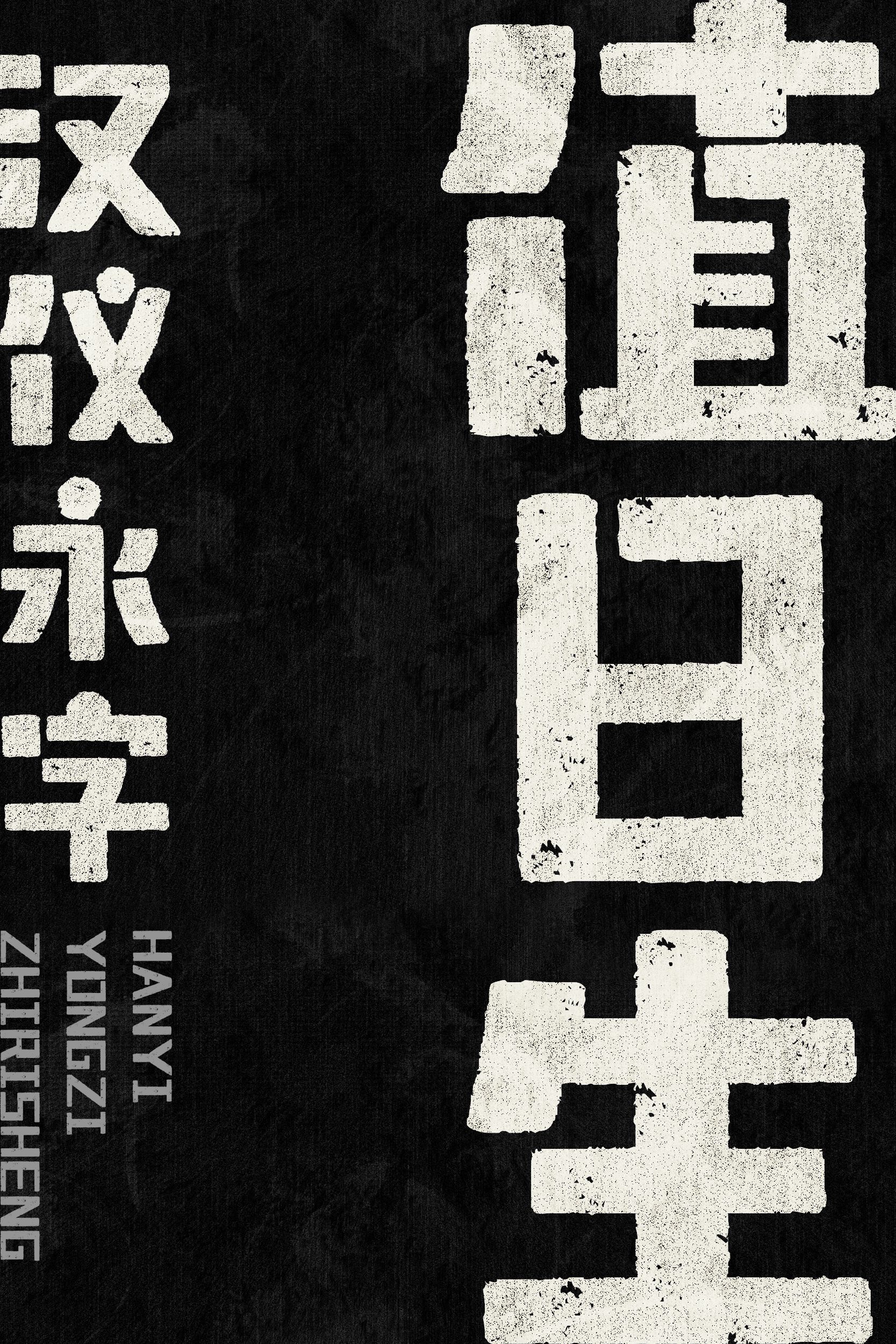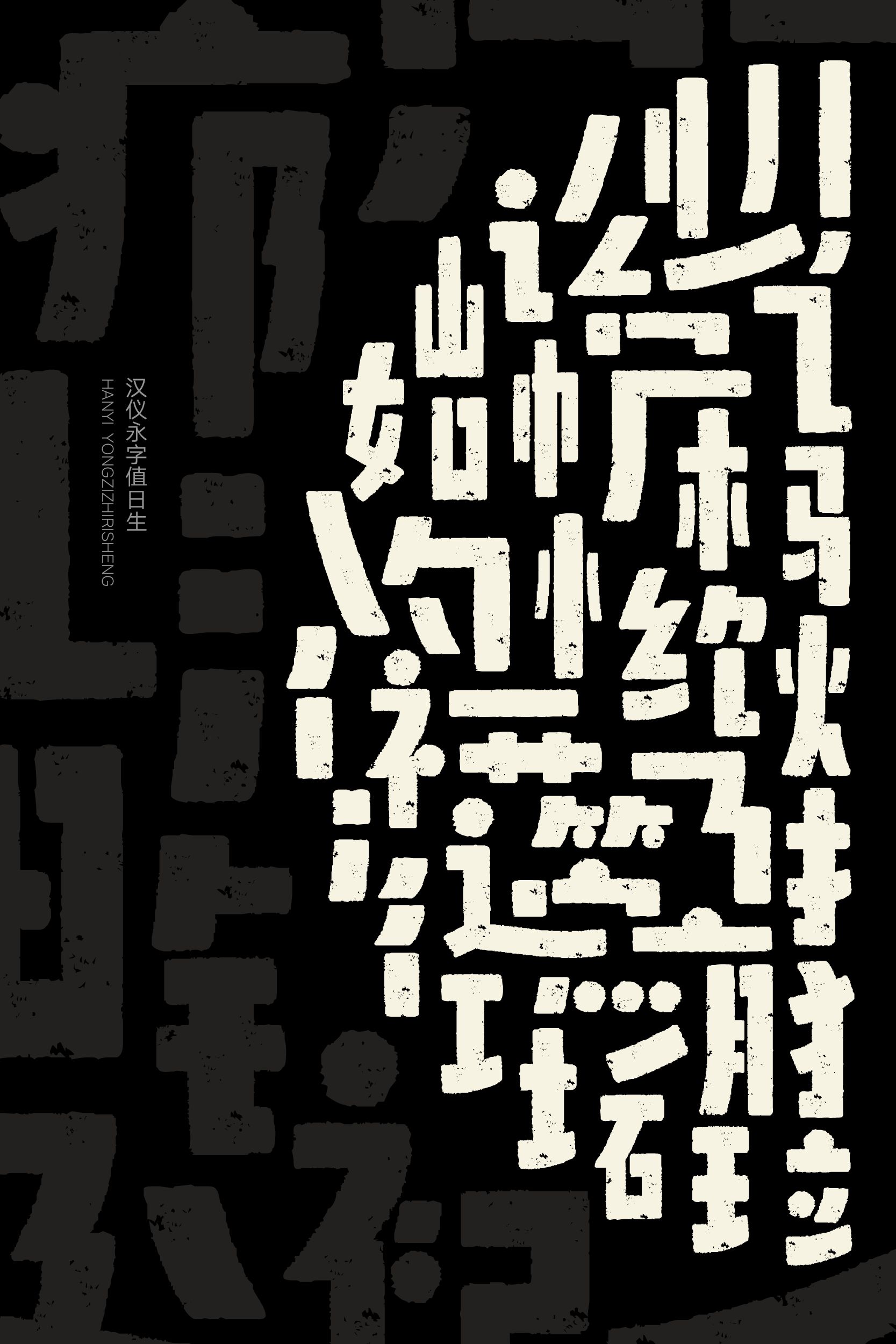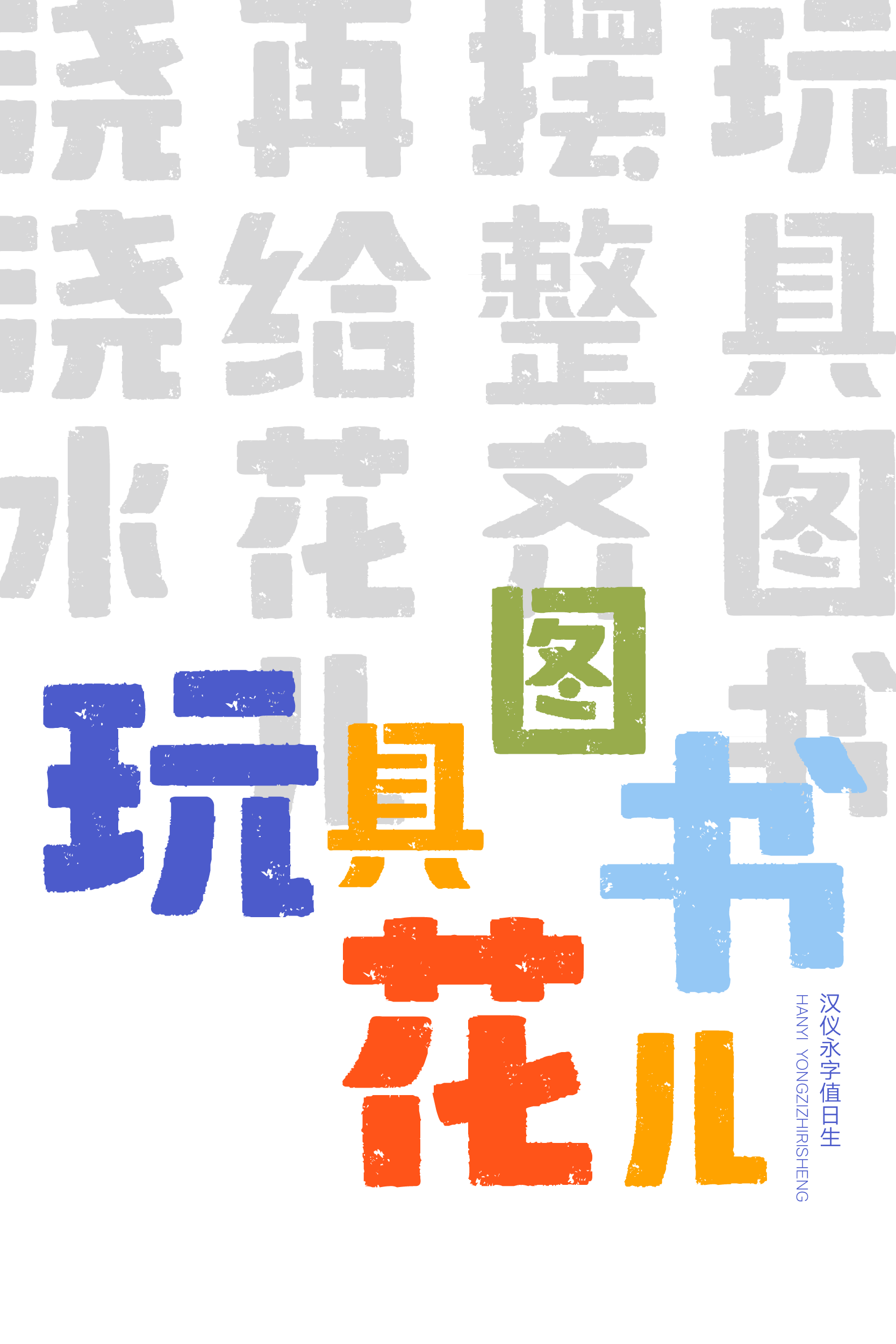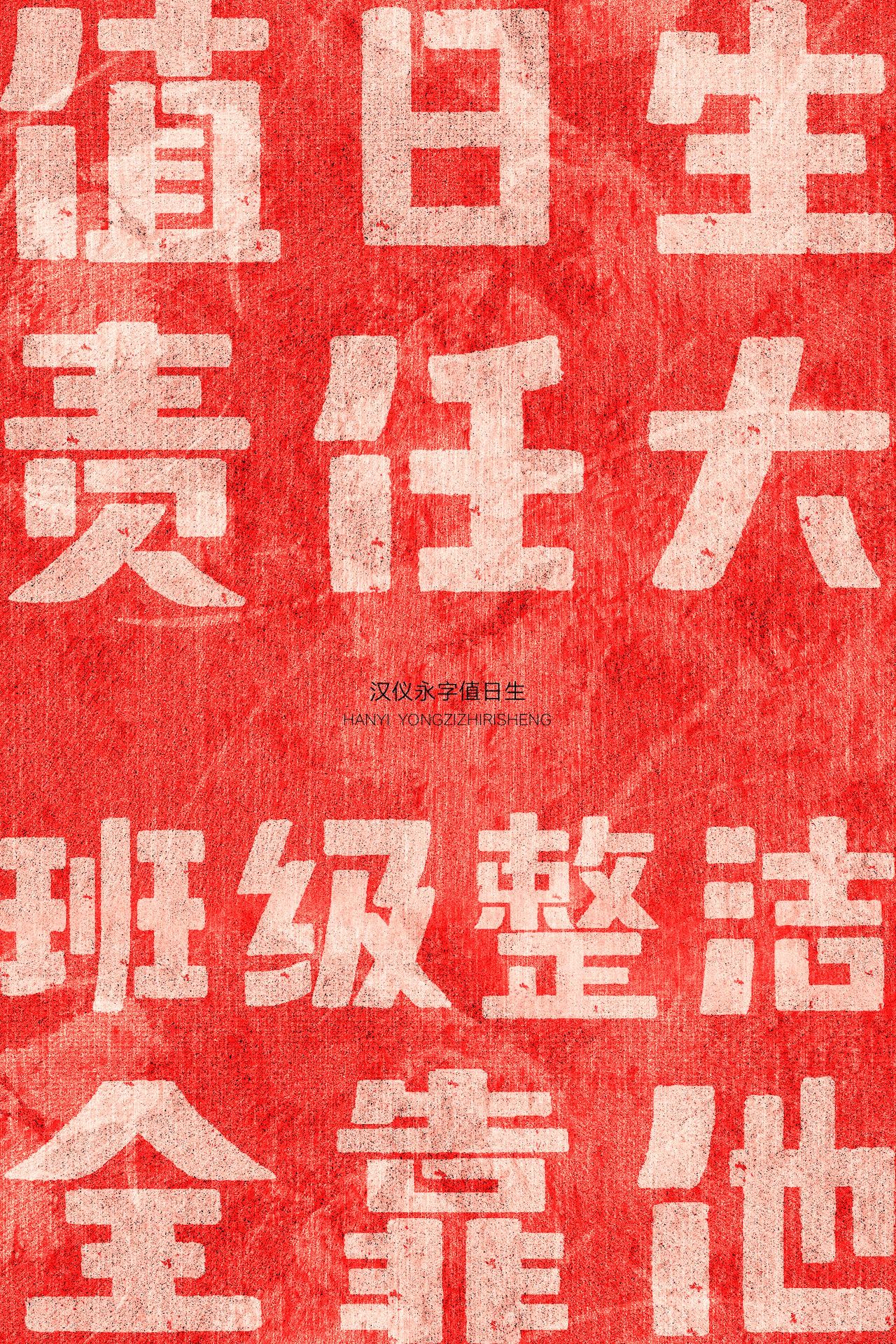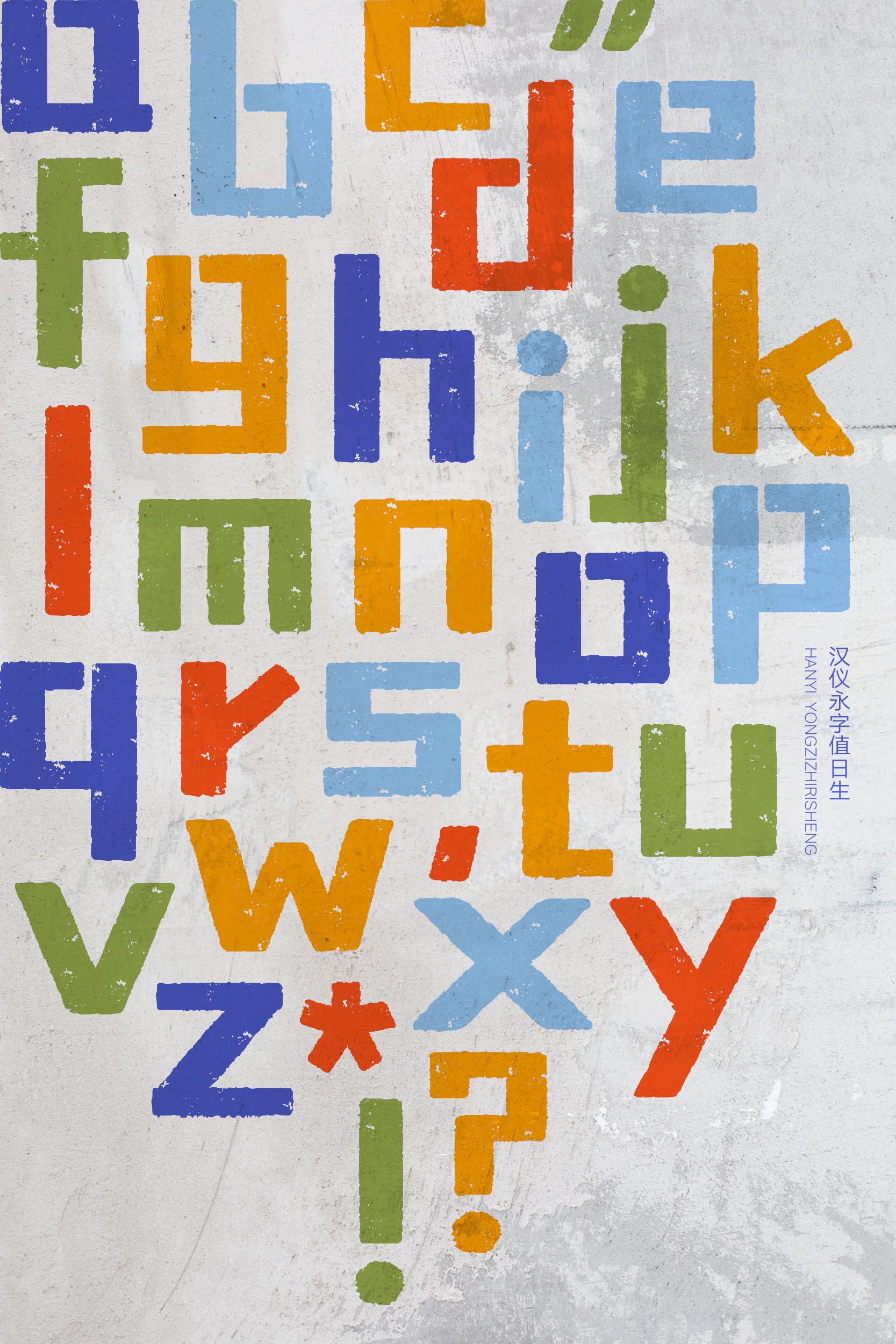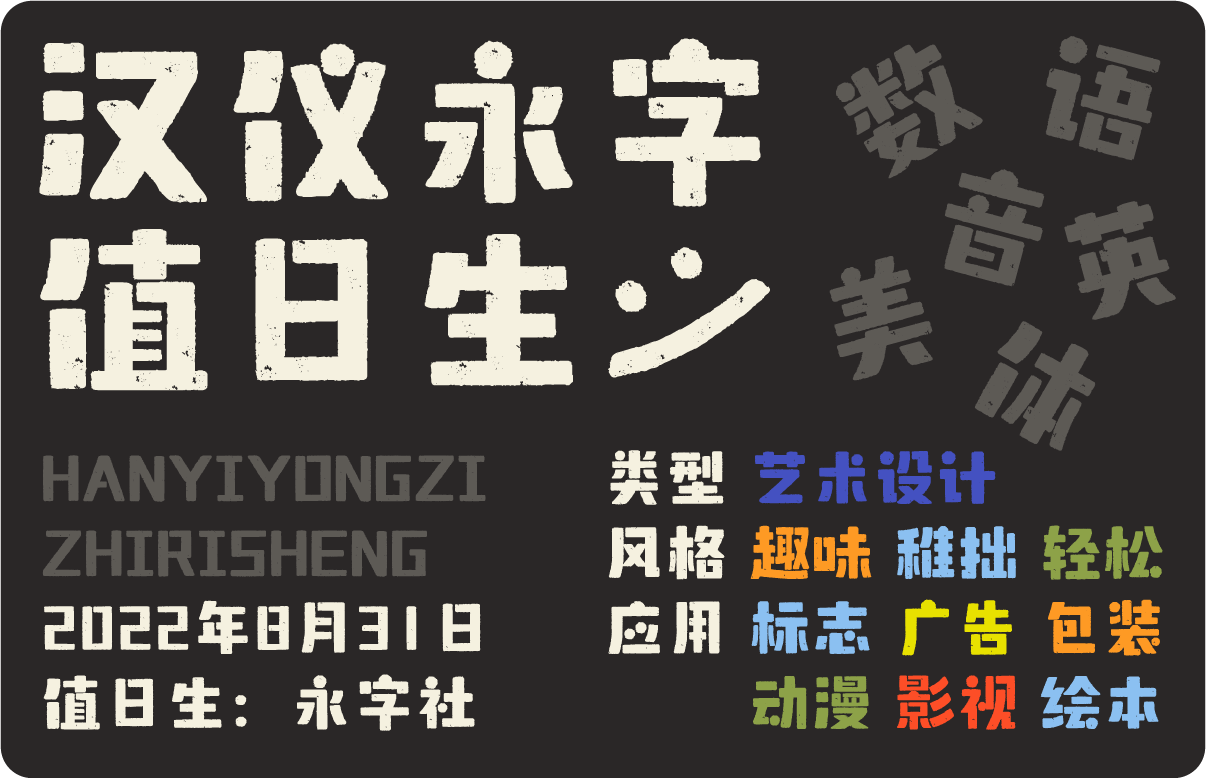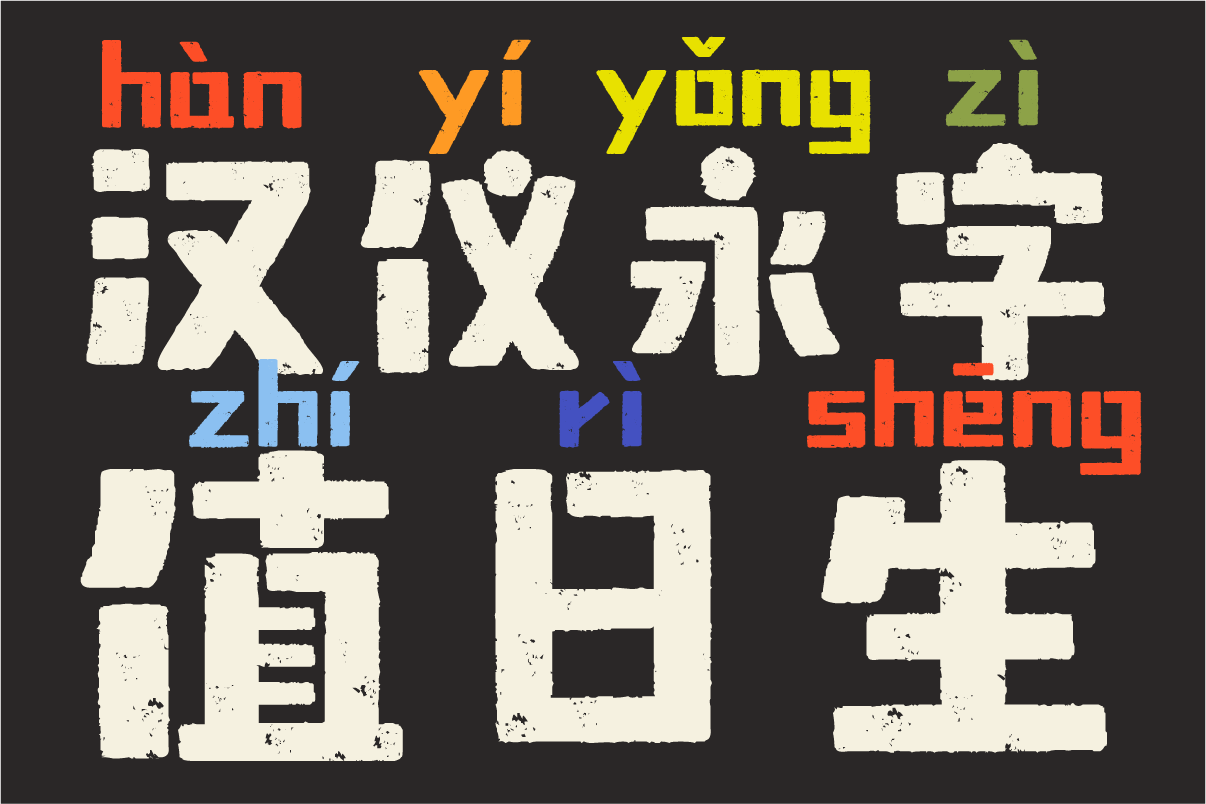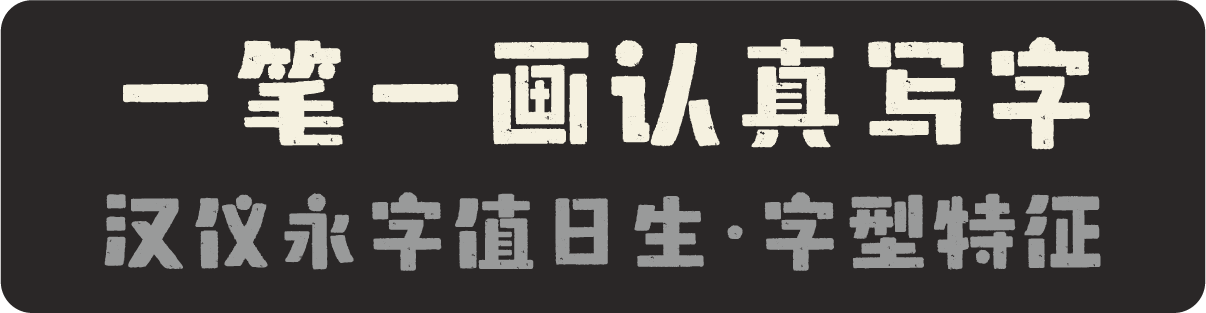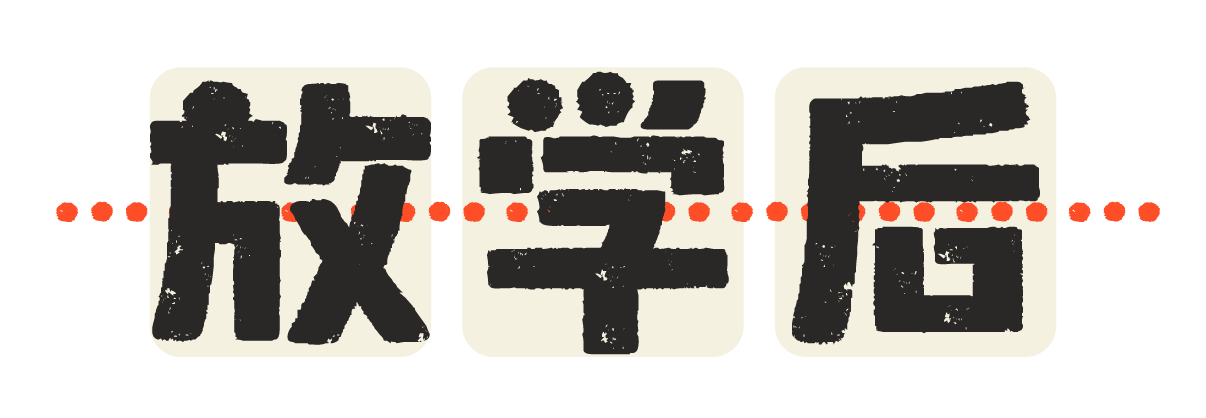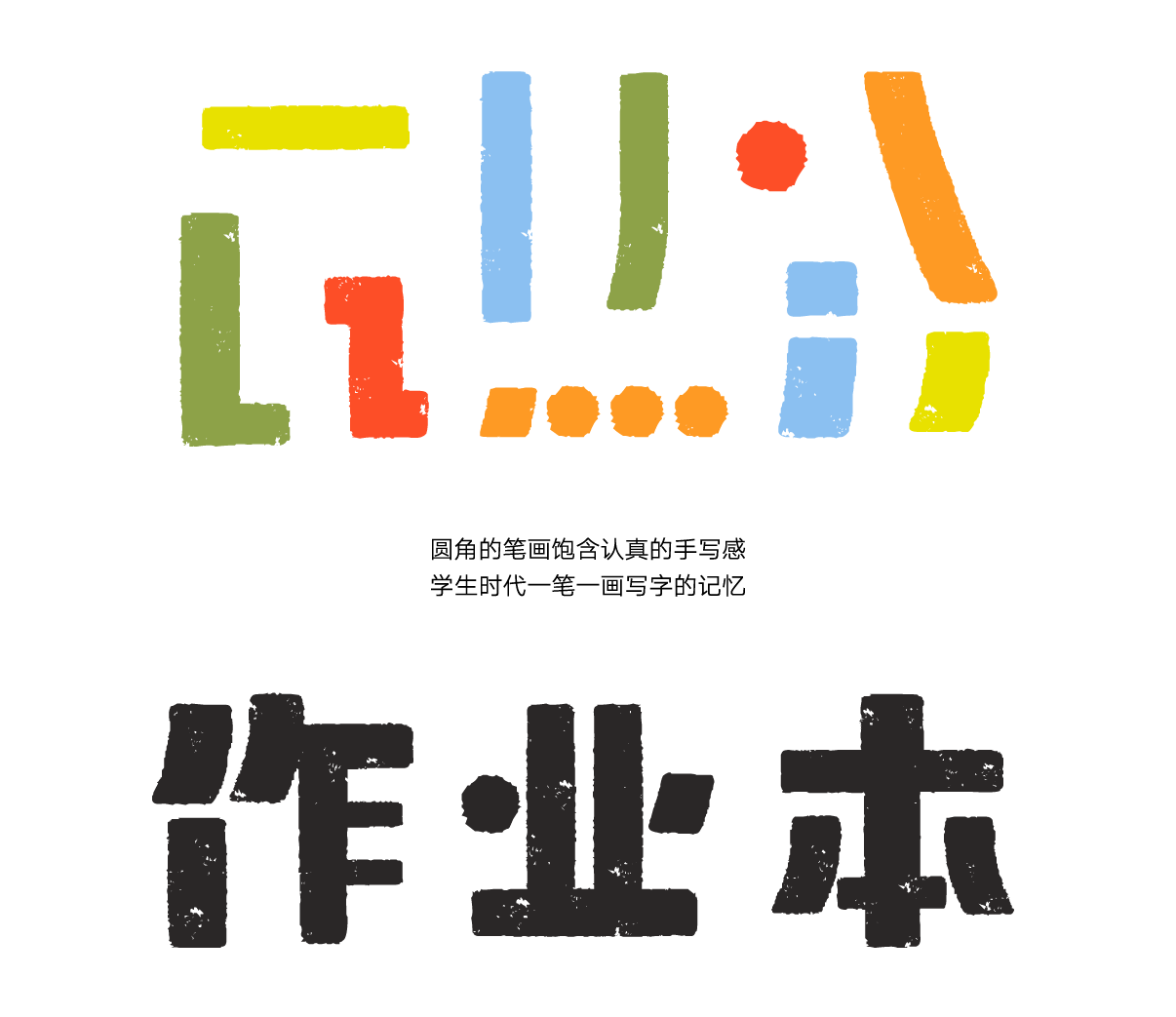
这款字体还原了无忧无虑的学生时代
还记得学生时代认真负责的值日生吗?一笔一画抄写的课程表、精心绘制的黑板报、粉笔与黑板摩擦的声音、放学后的欢乐时光……这些记忆,都被好好地收藏在汉仪永字值日生这款字体之中。汉仪永字值日生是由永字社创作的一款充满稚拙趣味的创意字体,一笔一画,还原无忧无虑的学生时代。
学生时代认真负责的值日生,写在黑板上的方块字规规矩矩、整整齐齐。
简洁概括的美术字风格,一笔一画,有方有圆。
还原黑板上粉笔字的颗粒质感,细节满分。
西文部分保留与中文部分一致的方块造型与圆点造型,风格统一。
汉仪永字值日生不只绘制学生时代的黑板报,还可以在成年的世界里唤醒沉睡的童心,适合作为标题字体应用于休闲娱乐的使用场景,营造轻松愉快的氛围。